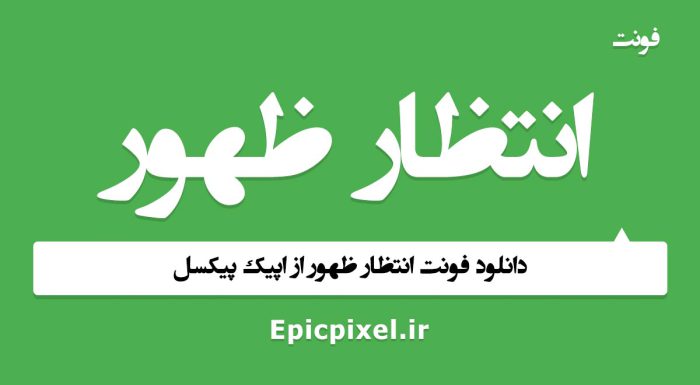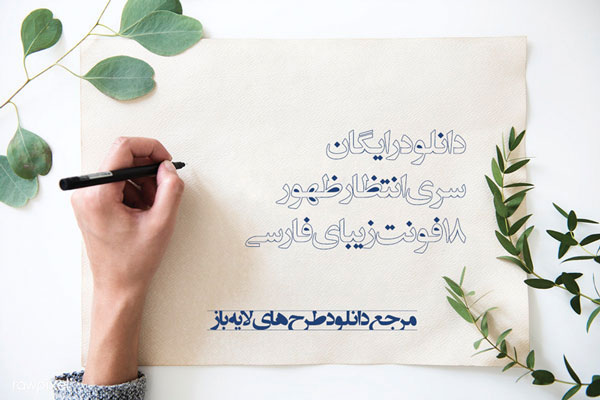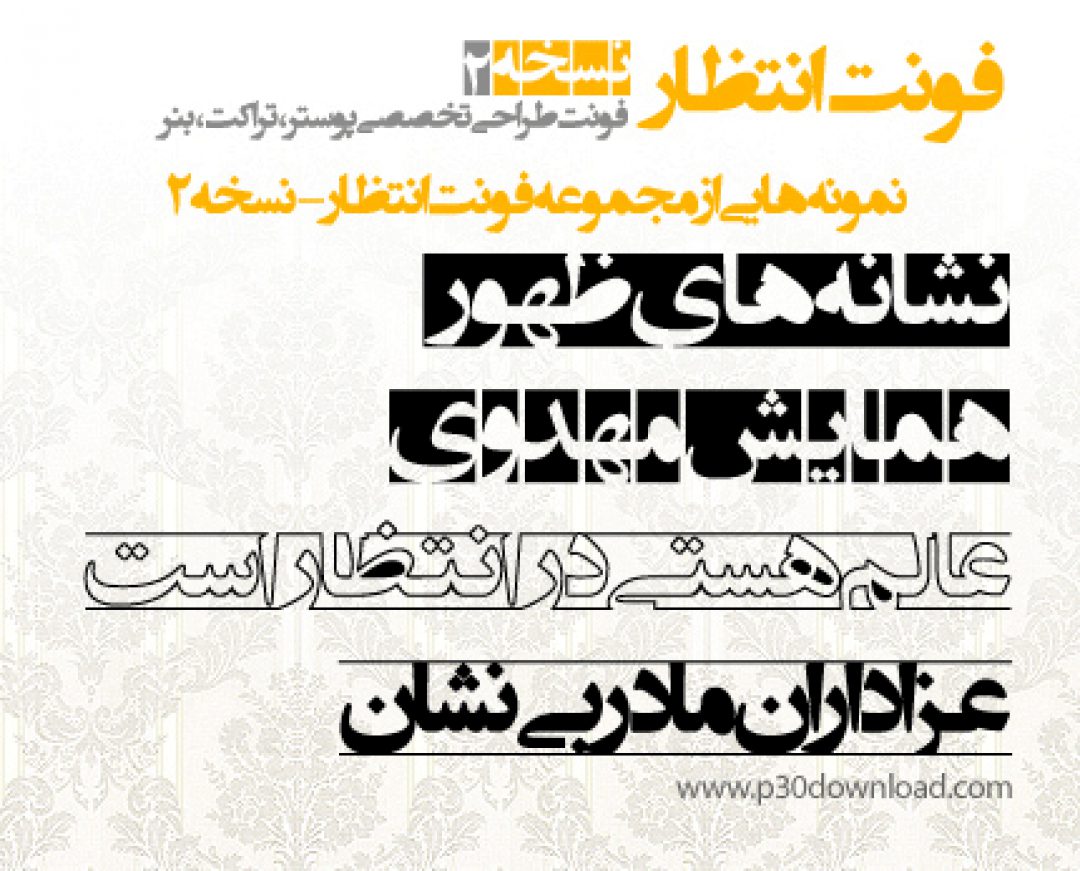
19 فونت انتظار ظهور فارسی
فونت انتظار ظهور نام یک مجموعه جدید و فوق العاده زیبا از قلم های فارسی است که در ۱۹ سبک مختلف (برخی منابع ۱۸ سبک را ذکر کرده اند) برای طراحان و علاقه مندان به دنیای گرافیک آماده شده است. این مجموعه بسیار زیبا و کم نظیر در میان فونت های فارسی زبان است که با دارا بودن سبک های متنوع و زیبا، امکان خلق طرح های دیدنی و خاص را فراهم می کند. فونت انتظار ظهور برای طراحی بنرها، ساخت عکس نوشته، تایپوگرافی و به ویژه طراحی پوستر ایده آل بوده و جلوه ای خاص و بی نظیر به طرح های شما خواهد بخشید. تمامی فونت های این مجموعه در فرمت TTF بوده و کاملاً رایگان و تست شده هستند.
فونت انتظار ظهور فارسی (۱۹ وزن): قلمی زیبا و رایگان برای طراحی
فونت انتظار ظهور یک مجموعه از قلم های فارسی است که با هدف ارائه ابزاری زیبا و کارآمد برای طراحان گرافیک ایجاد شده است. این مجموعه در حال حاضر شامل ۱۹ وزن (و یا ۱۸ سبک) متنوع است که هر یک ویژگی های بصری منحصربه فردی دارند. طراح این فونت “سایت کارهای فرهنگی” است و حجم فونت انتظار ظهور ۲ – ۱۳ نیز ۶۴ کیلوبایت ذکر شده است.
- تنوع سبک ها: این مجموعه با ۱۸ یا ۱۹ سبک مختلف عرضه شده است که شامل فونت هایی با ظاهر های متفاوت، از جمله فونت های توخالی (Outlined) و با خطوط موازی (مانند فونت انتظار ظهور ۲) می شود. این تنوع مدل ها به طراحان امکان می دهد تا برای نیازهای مختلف، از عنوان نویسی تا متون با جزئیات خاص، بهترین گزینه را انتخاب کنند.
- پشتیبانی از حروف زینتی: جهت افزایش زیبایی متن، می توان از حروف زینتی خاصی مانند “ی کشیده” (با کلید “ء همزه”) و “ـه” (با Shift+Z) استفاده کرد. این قابلیت به تایپوگرافی و ایجاد جلوه های خوشنویسانه در متن فارسی کمک شایانی می کند.
- کیفیت بالا و تست شده: فونت های این مجموعه دارای کیفیت بالا بوده و کاملاً تست شده هستند، که این امر اطمینان خاطر را برای استفاده در پروژه های حرفه ای فراهم می آورد.
- دارای اعداد فارسی: این ویژگی تضمین می کند که تمامی اعداد در متن شما نیز به فرمت فارسی صحیح نمایش داده شوند.
- شباهت به فونت تیتر: این فونت با شباهتی که به فونت محبوب “تیتر” دارد، به یکی از فونت های پرطرفدار در زمینه گرافیک و به ویژه امور مذهبی تبدیل شده است.
کاربردها: توسعه بصری در پلتفرم های مختلف
فونت انتظار ظهور با تنوع سبک ها و ویژگی های بصری برجسته، برای طیف وسیعی از کاربردها در محیط های چاپی و دیجیتال مناسب است:
- طراحی گرافیکی و تبلیغات:
- طراحی پوستر و بنر: این فونت به عنوان یکی از زیباترین فونت های فارسی برای طراحی پوستر شناخته می شود و برای ایجاد بنرهای تبلیغاتی و اطلاعیه ها بسیار کارآمد است.
- ساخت عکس نوشته و تایپوگرافی: برای خلق عکس نوشته های جذاب و انجام پروژه های تایپوگرافی که نیاز به جلوه ای خاص و هنری دارند، ایده آل است.
- طراحی کارت ویزیت و تراکت: مناسب برای طراحی عناصر چاپی مانند کارت ویزیت و تراکت که نیاز به خوانایی و جذابیت بصری دارند.
- تولید محتوا و نشر:
- عنوان و تیتر نویسی: به دلیل تنوع مدل ها، برای عنوان نویسی و تیترهای پرقدرت در مجلات، روزنامه ها و وب سایت ها کاربرد فراوانی دارد.
- اطلاعیه های مذهبی: به دلیل شباهت به فونت تیتر و زیبایی خاص خود، در امور و اطلاعیه های مذهبی بسیار محبوب است.
- سازگاری با پلتفرم ها: این فونت قابل استفاده در تمامی نرم افزارهای طراحی چه با گوشی موبایل و چه با کامپیوتر است. این سازگاری گسترده آن را برای انواع طراحی های چاپی و غیرچاپی با کیفیت مناسب می سازد.